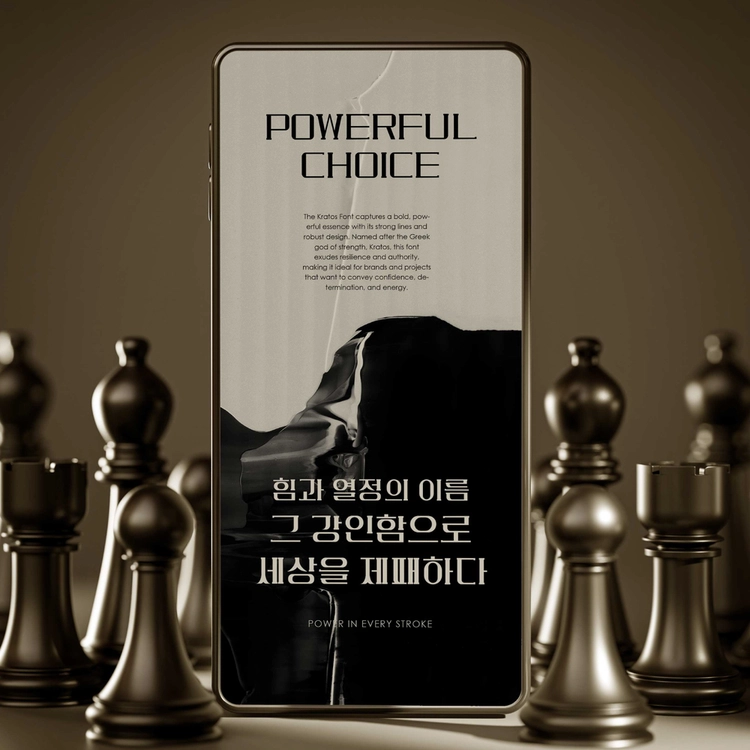
크라토스 폰트는 힘과 강인함을 상징하는 게임 "God of War"의 전투의 기운을 담았습니다. 굵은 선과 담대한 디자인으로 구성되어 있어 카리스마 있는 분위기를 잘 전달합니다. 이 폰트는 액션 웹툰이나 격투 게임의 로고 등 힘과 권위를 담은 분위기에 잘 어울립니다.